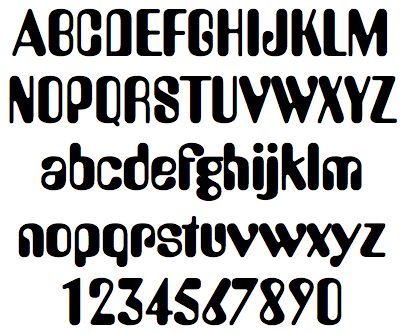
Ah ja, interessant. Dann ist die A 770 tatsächlich wohl eine eigene Variante von URW gewesen. Die hatten ja die ganzen Schriftendateien von diversen Herstellern im Zugriff. Die Schrift stammt von der infinity library.
Ich war grad noch ne halbe Stunde im Internet und durfte feststellen, dass das Kind Amelia viele Väter zu haben scheint. Entweder war der Autor so geschäftstüchtig, oder er ist kräftig über den Tisch gezogen worden. Und dann waren natürlich auch die Trittbrettfahrer unterwegs und haben das Süpplein aufgewärmt.
Bei Identifont kennt man drei Versionen:
– Amelia (Bitstream) von Stanley Davis von 1967
– Amelia Linotype von Stanley Davis von 1965
– Amelia (Font Company) von 1992
Bei MyFonts findet man sie auch:
– Amelia von Stanley Davis, Jahr 1967 für VGC, Publisher: Bitstream
U.a. bei Fontspace wird sie als Freefont gehandelt:
– Amelia Font by Allen R. Walden (!?)
Hierzulande gab es dann
– mindestens eine Fassung bei E+F oder URW (hab ich bei mir leider nicht gefunden), und
– schließlich die gerade und kursivierte Version nebst Outline und Shadow als „Deco A 770“ unter dem Namen „infinitype“ (Auszug des afm-files aus meinem Giftschrank: Generated by Fontographer 4.1 26.09.99 – Copyright 1990-1993 Brendel Informatik & SoftMaker Software GmbH. All rights reserved.)